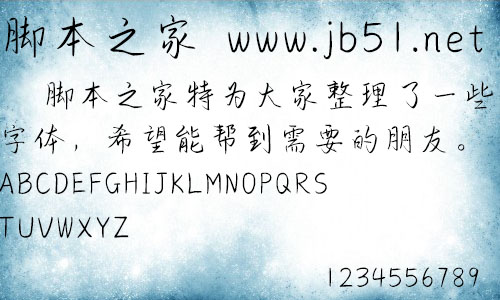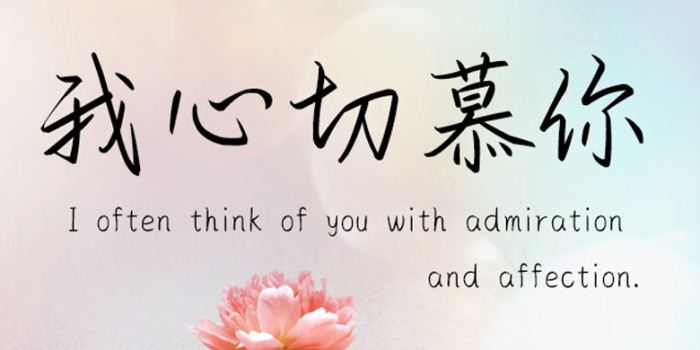
方正手跡-我心切慕你由方正字庫王航設(shè)計(jì)師出品的藝術(shù)字體,該字筆畫連貫流暢,連筆的添加恰到好處,整體筆畫挺拔有力,文藝的同時(shí)不失力量,具有很好的視覺感,適合應(yīng)用于藝術(shù)設(shè)計(jì)、平面宣傳設(shè)計(jì)、網(wǎng)頁設(shè)計(jì),書法等領(lǐng)域。
我心切慕你是一款文藝感十足的行書體。該字體筆畫連貫流暢,連筆的添加恰到好處,整體筆畫挺拔有力,文藝的同時(shí)不失力量。適用于文藝類的書刊、品牌廣告和產(chǎn)品包裝設(shè)計(jì),以及社交網(wǎng)絡(luò)的個(gè)性化用字。。